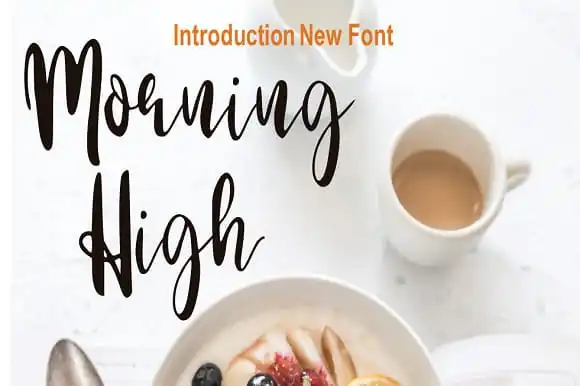
Morning High Script Font – Download Grátis
A Morning High Script Font é uma elegante caligrafia escrita à mão que oferece flexibilidade para designers criativos. Com seu estilo natural e único, essa fonte se destaca como um recurso versátil para projetos diversos. Suas características delicadas e aconchegantes tornam-na perfeita para adicionar um toque autêntico e encantador a qualquer design. Independentemente do projeto que você estiver criando — seja em logotipos, cartazes ou designs digitais — essa fonte está preparada para transformar suas criações com sua graça única e personalidade peculiar. Experimente esta maravilhosa fonte e descubra os infindáveis possíveis combinações que ela pode criar.